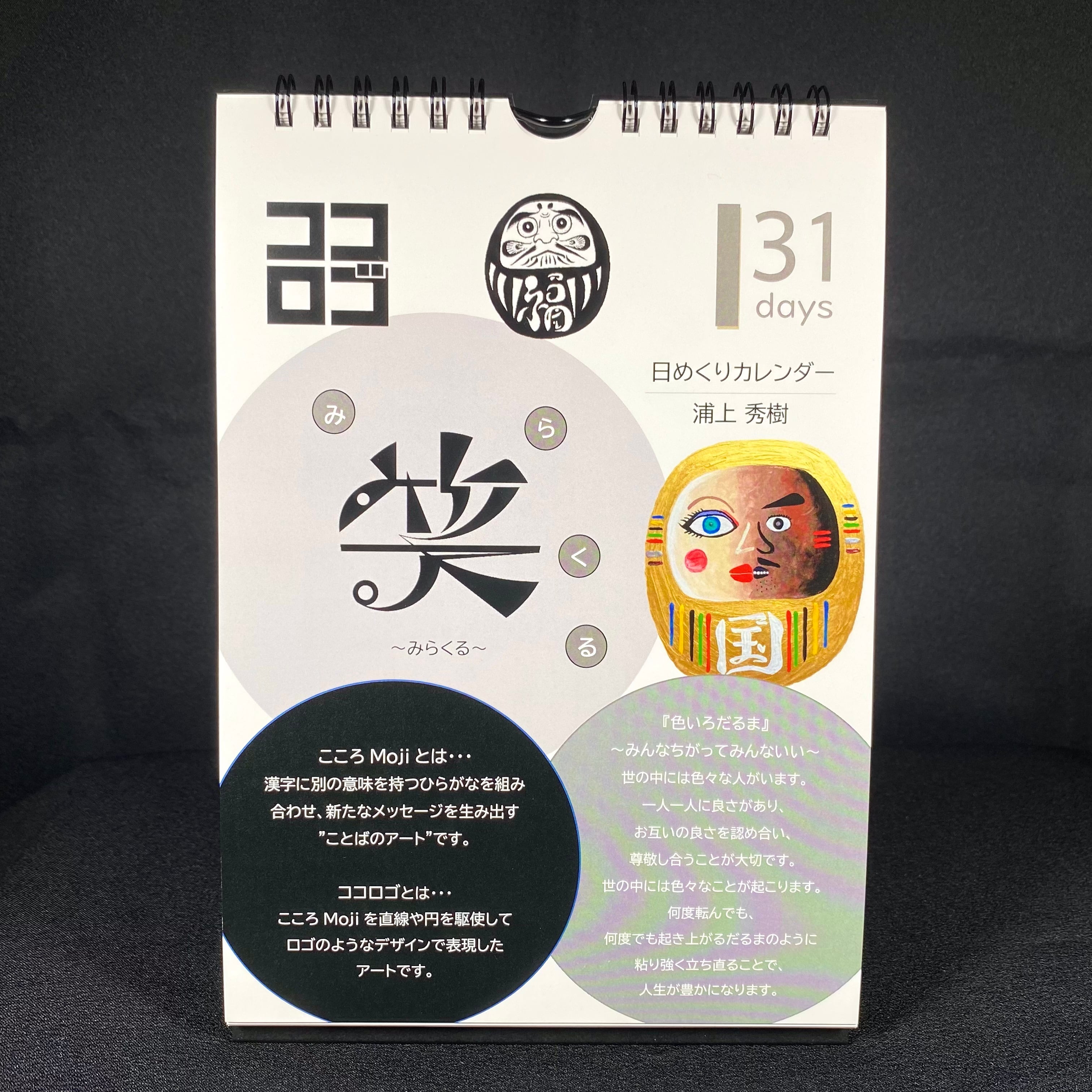
こころMoji 日めくりカレンダー (色いろだるま&ココロゴバージョン)
こころMojiの日めくりカレンダーに色いろだるま&ココロゴバージョンが登場!
こころMojiとは、
●漢字
●ひらがな
●解説(こころ)
からできています。
今回、この日めくりカレンダーには
1ヶ月分(31日)の色いろだるまとココロゴが書かれています。
ココロゴとは・・・
こころMojiを直線や円を駆使してロゴのようなデザインで表現したアートです。